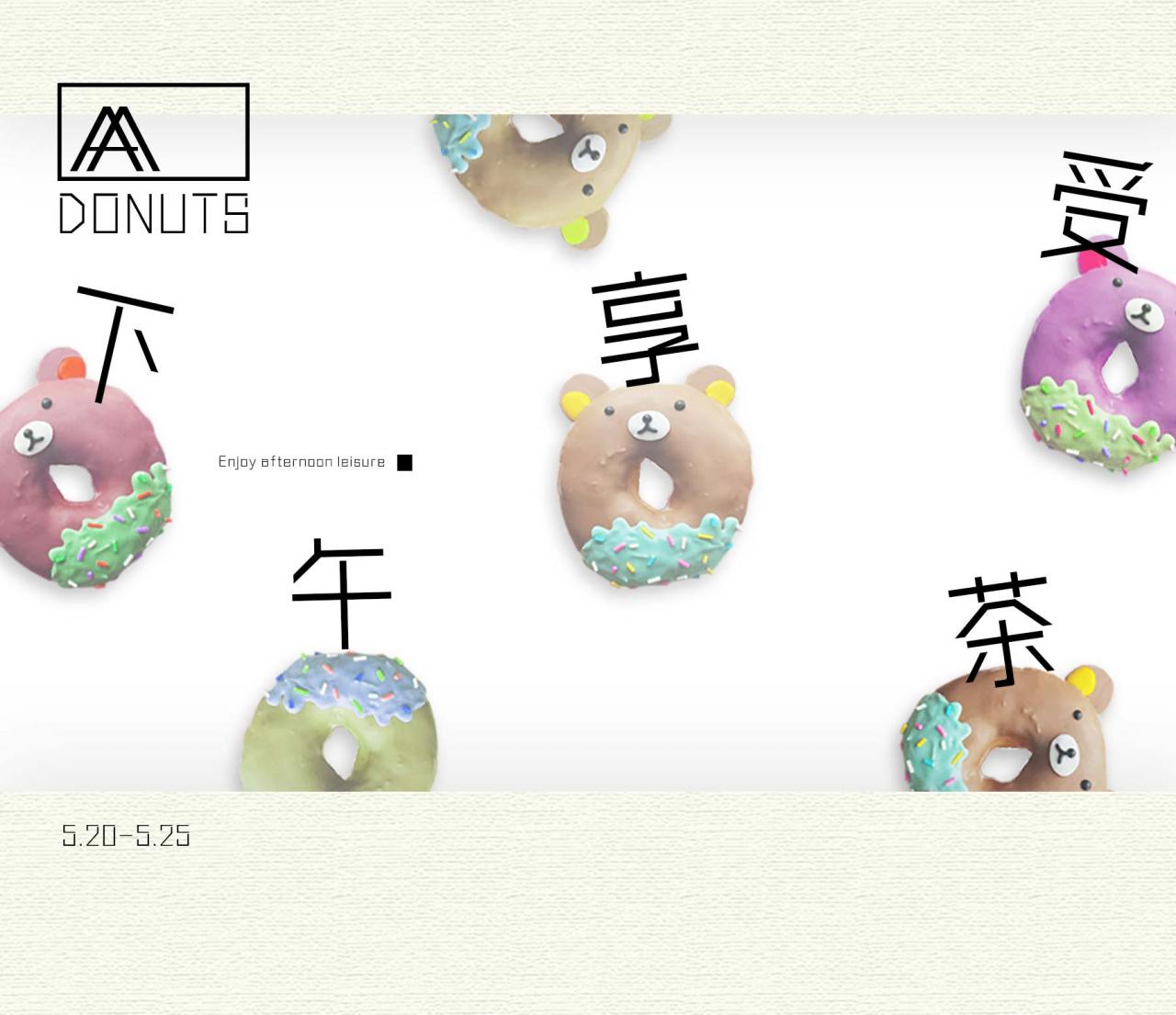
三极清雅细黑简体
字体名称:三极清雅细黑简体
设计师:蔡荣富
所属分类:黑体
三极清雅细黑简体是一款适合于报刊与杂志排版应用的文字,该字体具有端正、简洁的特点。笔画整体看上去比较匀称,给人一种“宁静以致远,淡泊以明志”的舒适感。字体应用性强,可应用于报刊、杂志、品牌形象、包装、广告等领域。
适用媒介:杂志、书籍、广告、标志、宣传册、包装、影视、动漫、交互设计。